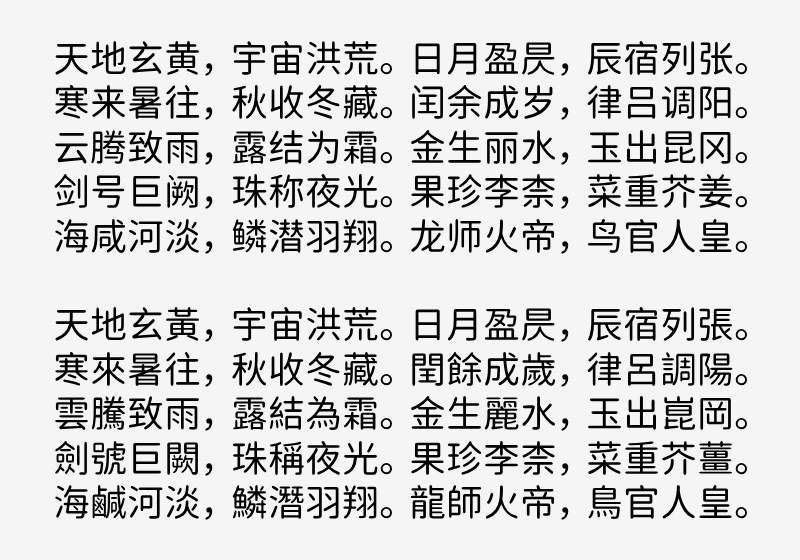
有爱圆体
有爱圆体(Nowar Rounded)是专门为《魔兽世界》和经典怀旧服制作的游戏界面字体。它由 Noto Sans 和资源圆体(Source Han Rounded)结合衍生而来,既保留了思源黑体规整易读的结构,也延续了资源圆体柔和圆润的字形特点。
这款字体针对游戏 UI 做了细致适配,提供 Light、Regular、Medium、Bold 四种常用字重,覆盖标题和正文等不同显示场景。虽然字重数量比资源圆体更少,但已经足够满足游戏内各类文字的层级展示需求。
字体风格
有爱圆体整体风格清爽柔和,在保证高辨识度的同时,把笔画转角和末端都处理得更加圆润,让原本偏冰冷机械的游戏界面变得更温和友好,长时间游玩也不容易视觉疲劳。